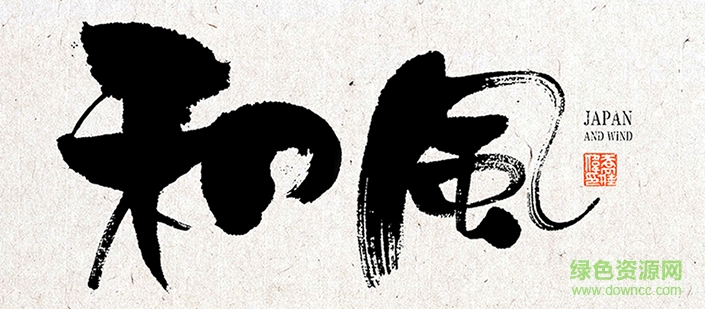
和風(fēng)字體是一款日本和風(fēng)書法字體,字跡飄逸灑脫,盡顯日式浪漫氣息,融入中文字體讓人感受文化的相融,很有藝術(shù)美感,綠色資源網(wǎng)誠意推薦!
和風(fēng)亦指“日本”風(fēng)味、日本式的意思。例如從西方傳過來的東西叫做“西洋風(fēng)”,從中國傳過去的就叫做“中國風(fēng)”。
因為日本是“大和”(やまと)民族,所以叫和風(fēng),就有很多“和風(fēng)”、“和味”、“和式”的東西了。如:“和風(fēng)音樂”、“和味飲食”、“和式喜好”、“大和風(fēng)情”、“和風(fēng)傳統(tǒng)”等。
和風(fēng)的特點是大多以碎花典雅的色調(diào)為主,帶有古樸神秘的色彩。